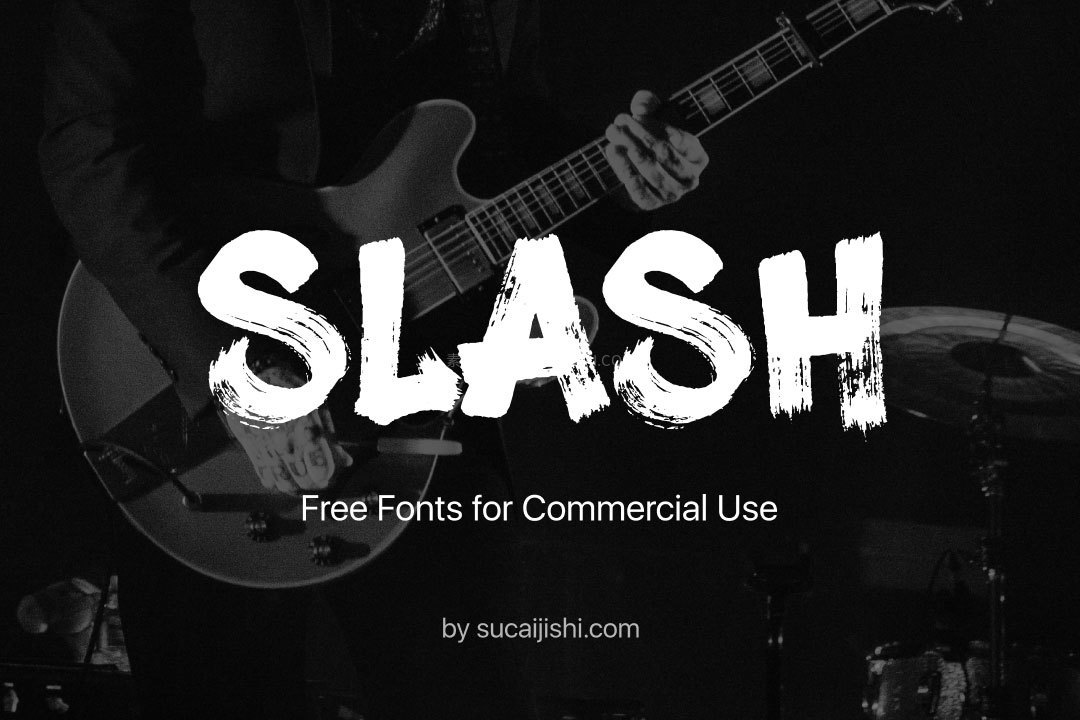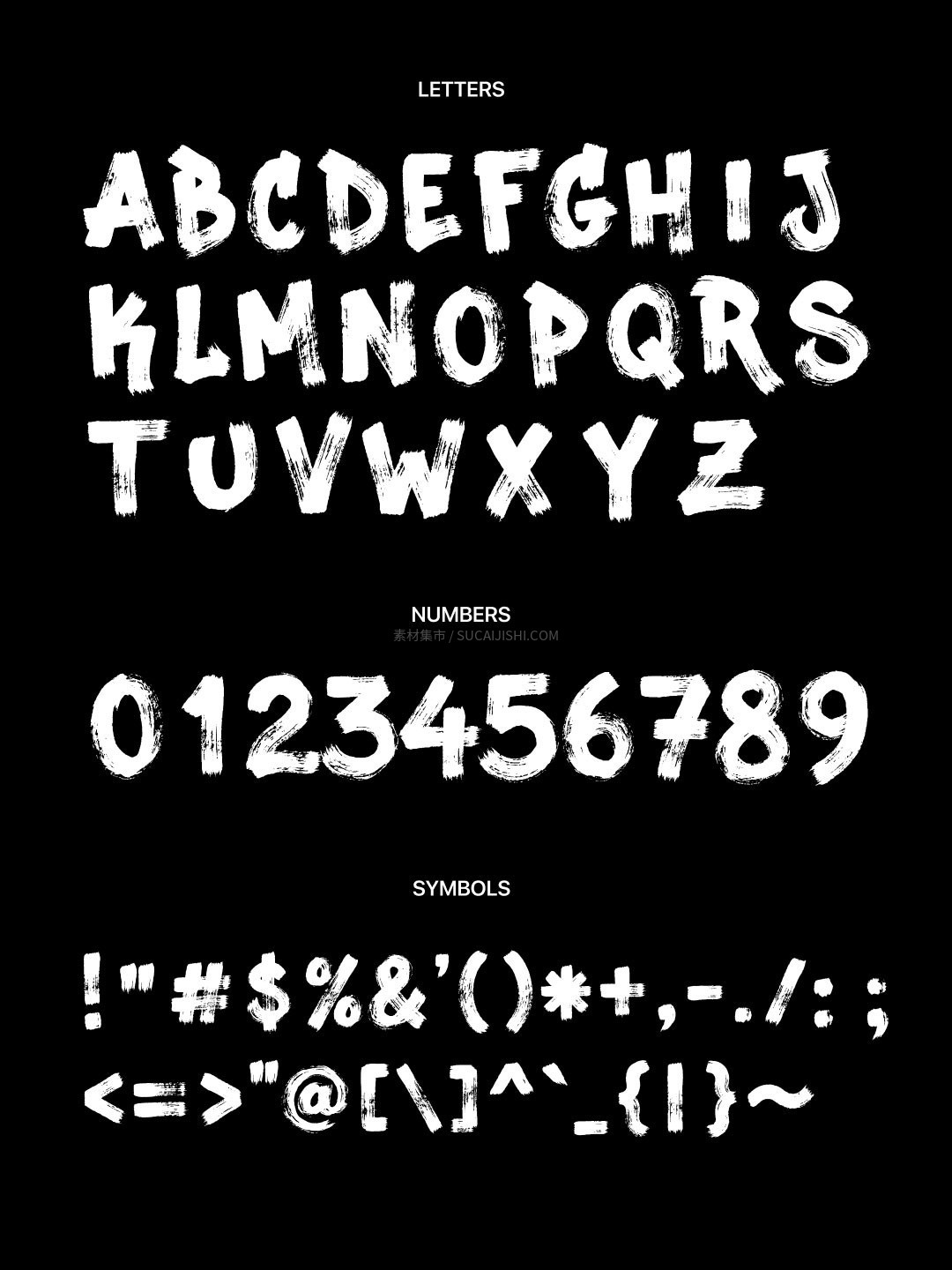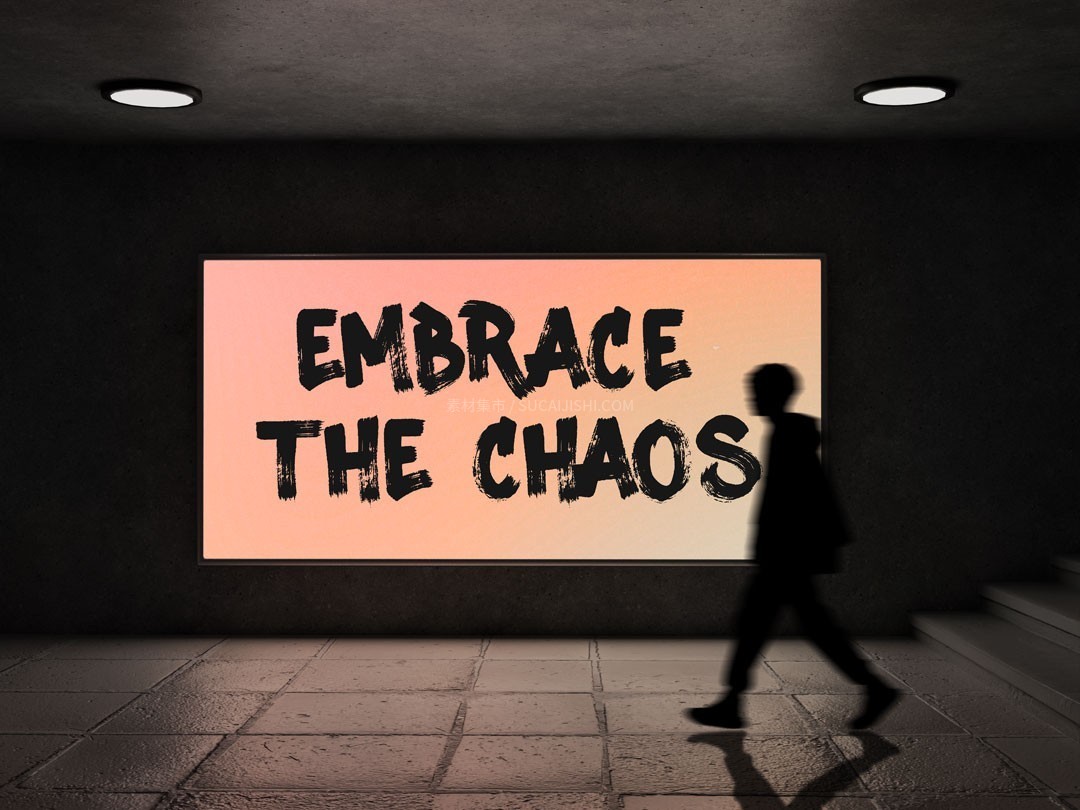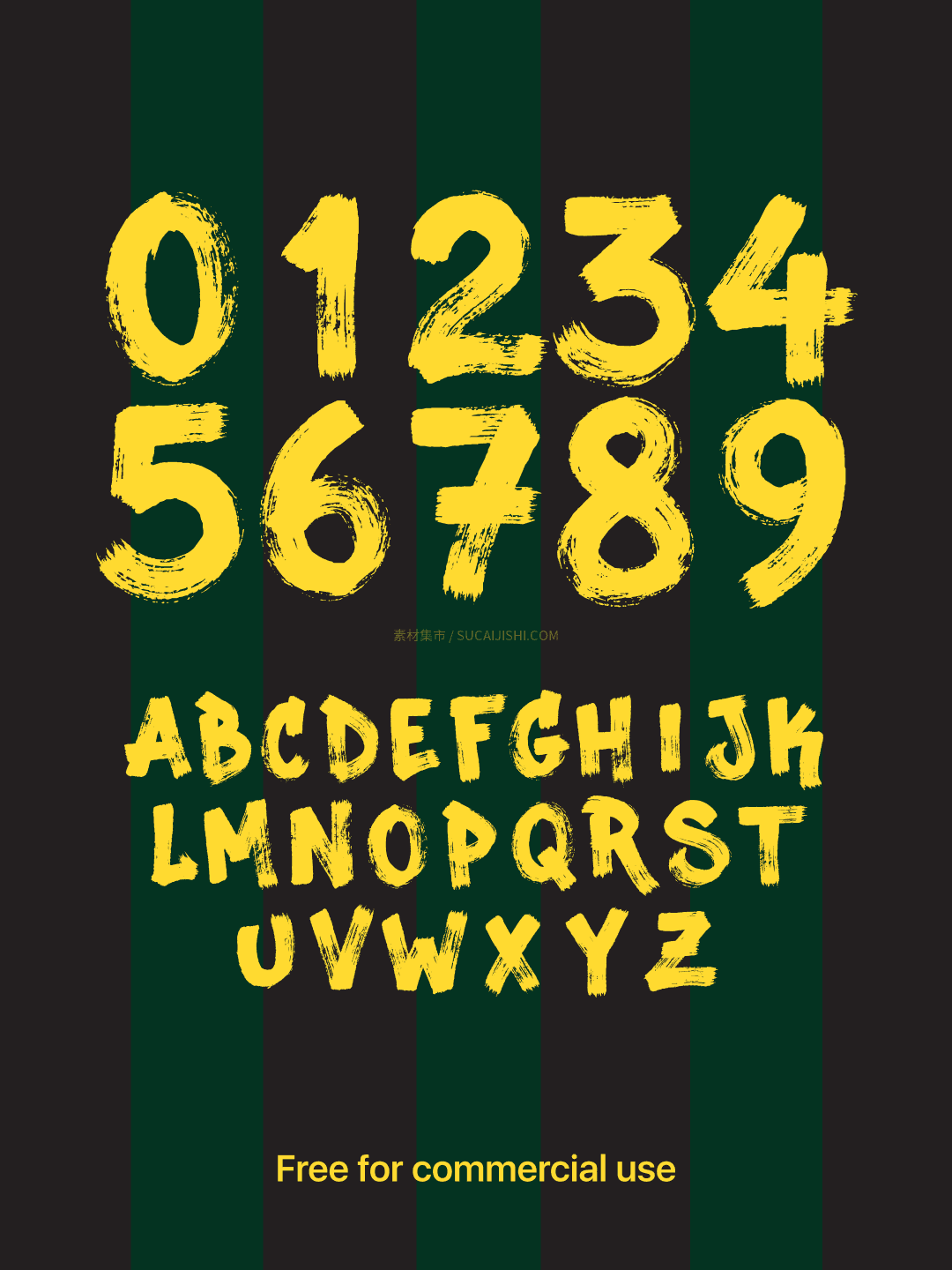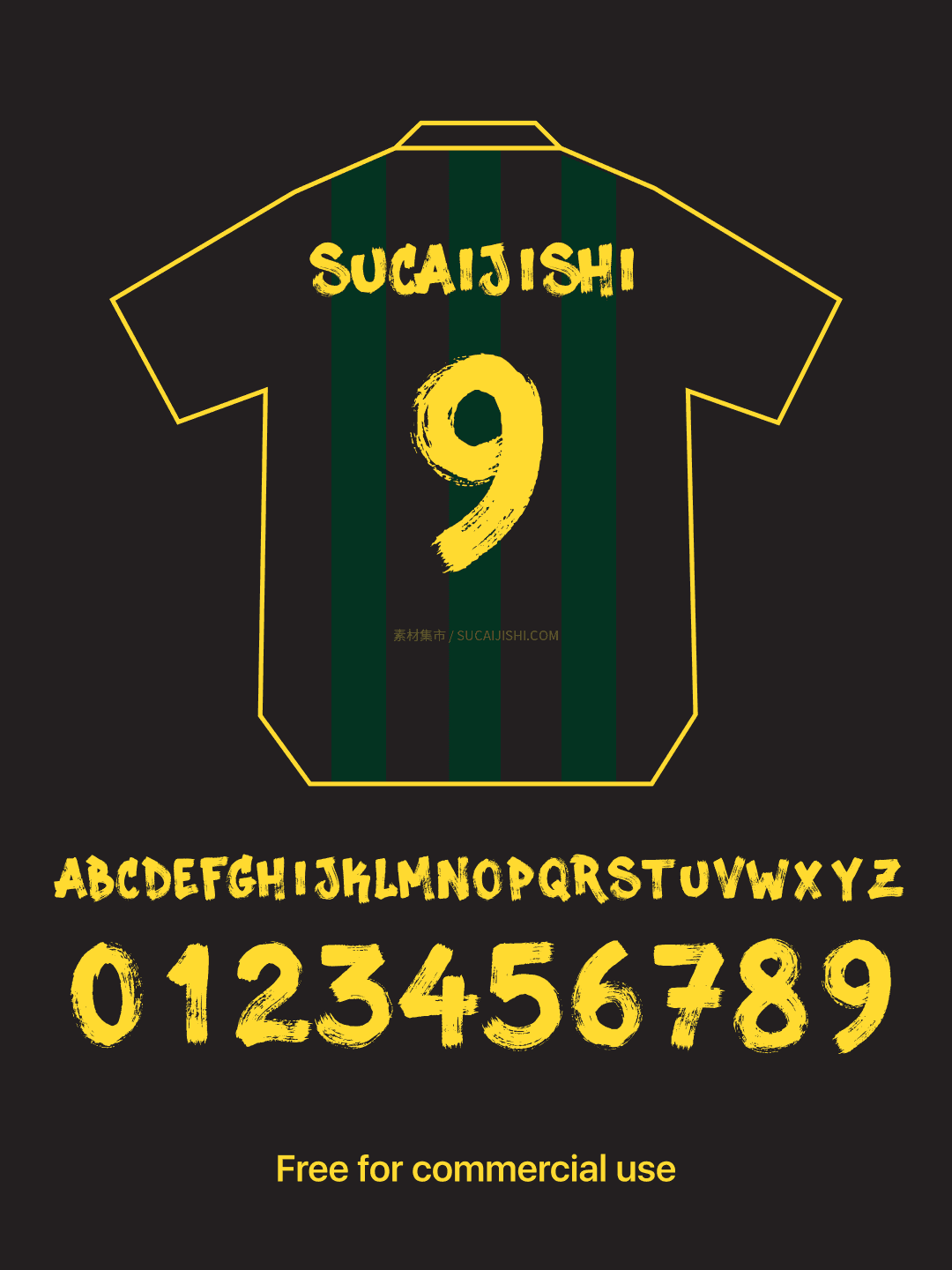
Sucaijishi Slash 免费商用手刷数字字体
Sucaijishi Slash是一款由素材集市原创发布的高品质手刷风格英文字体。这款字体保留了真实粗犷的笔刷纹理与墨迹飞白效果,极具力量感与街头张力。字体不仅包含完整的英文字母,还特别针对号码数字进行了精心设计,视觉冲击力十足。无论你是进行个人艺术创作还是全渠道商业项目,本套字体均提供无限制的免费商用授权。
适用场景:球衣号码设计、体育竞技海报、街头潮流服饰、品牌标志(Logo)设计、包装视觉、活动主KV等